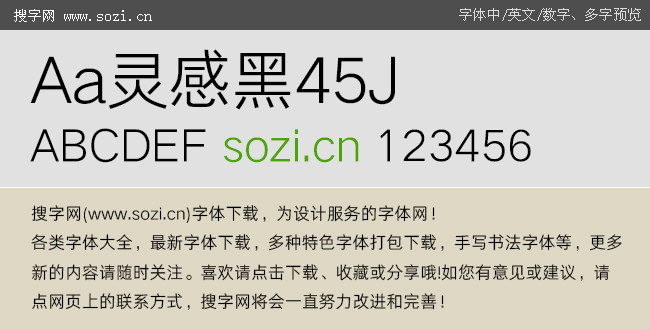
Aa靈感黑45J
搜字網(wǎng)給大家提供一款A(yù)a靈感黑45J(非商業(yè)使用)中文字體下載,該字體是一款中文黑體字體,整體字形方正,剛?cè)嵯酀?jì),優(yōu)雅大方,共有五款字重,從細(xì)到粗分別是35J、45J、55J、65J、75J, 字體流暢自然,適合書裝設(shè)計、海報設(shè)計等應(yīng)用(此字體為個人非商用版,商用可以聯(lián)系QQ:1006760504)。